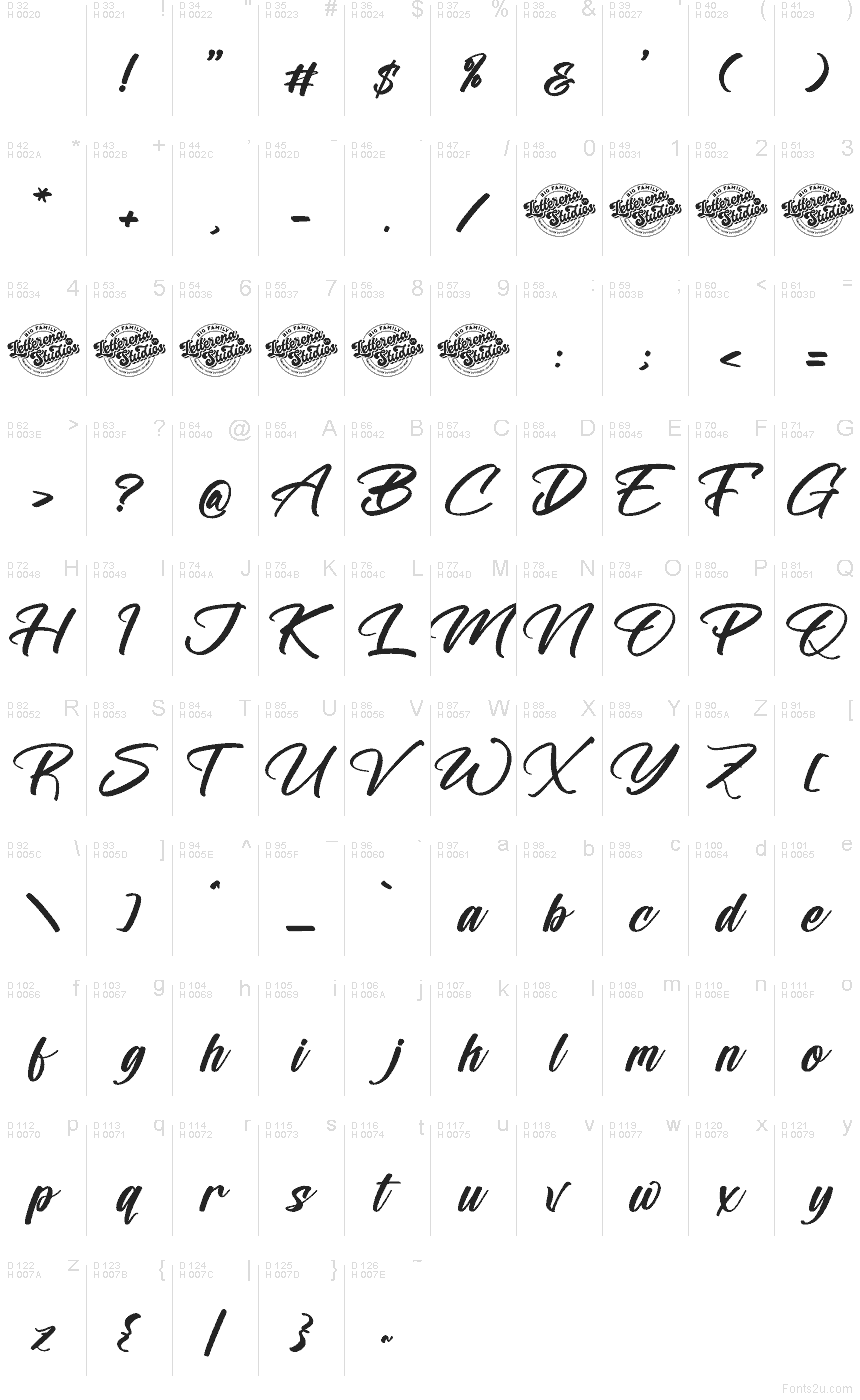
Malbonte Blackwell DEMO VERSION
Malbonte Blackwell, bezpłatny kaligraficzny krój pisma od Glorytype, stawia na nowoczesny styl typu script z długimi, zamaszystymi liniami początkowymi i grubymi, wyrazistymi łukami. Litery są płynne i modne, z wysoką wielką literą na początku i zwartymi małymi literami, co nadaje całości żywy, a nie formalny charakter.
Ten darmowy font świetnie sprawdzi się na opakowaniach produktów kosmetycznych, w logotypach butików, menu kawiarni, cytatach w mediach społecznościowych oraz nagłówkach, gdzie szybki, odręczny akcent może ożywić kompozycję. Doskonale nadaje się również do krótkich tytułów lub monogramów, ponieważ wydłużone pociągnięcia i staranne połączenia nadają nawet krótkim słowom pełny, elegancki wygląd.
Malbonte Blackwell, stworzony przez Glorytype, to bezpłatny kaligraficzny krój pisma.